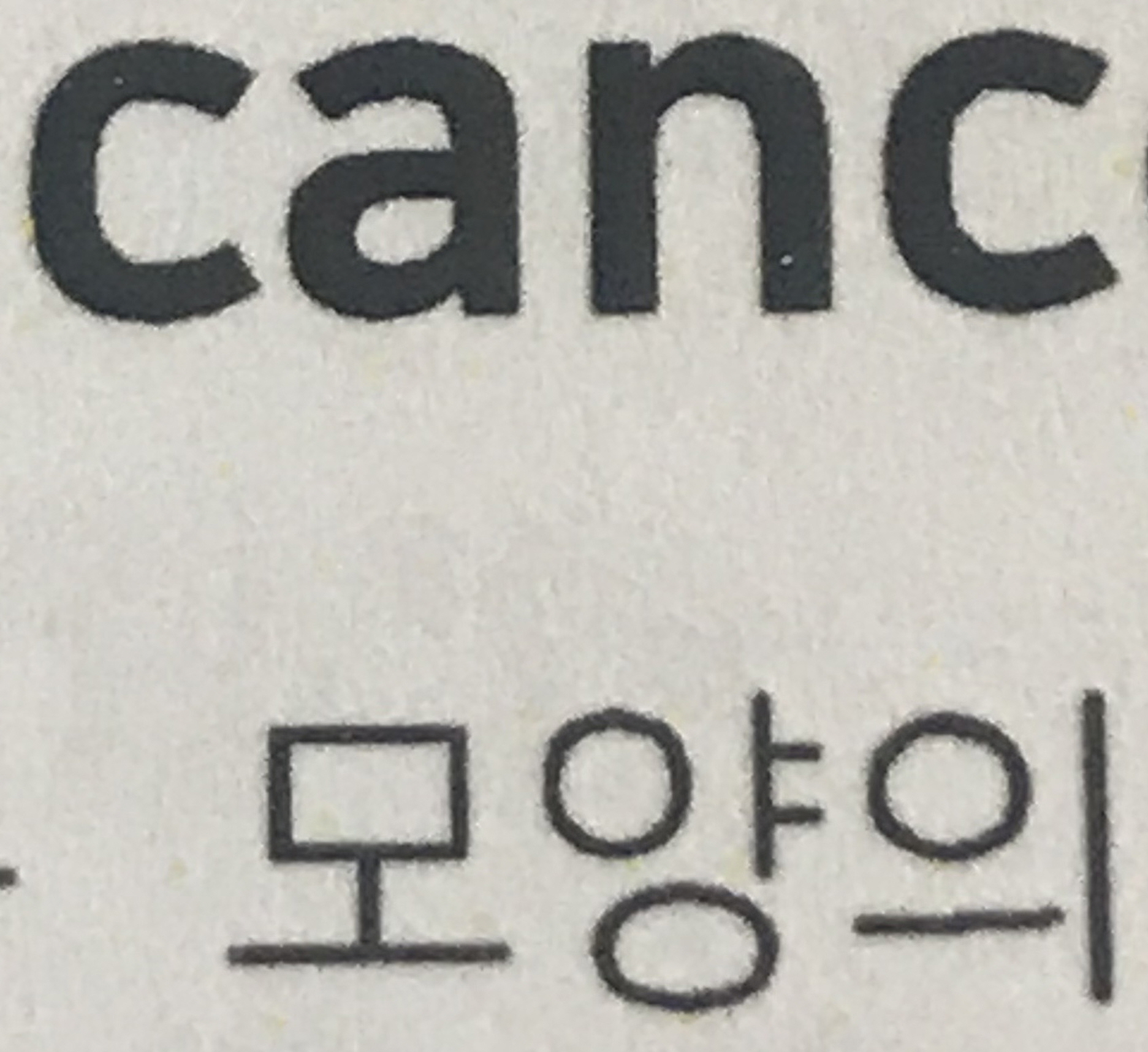
이거 폰트 kyl*** 2023.12.29 이거 무슨 폰트인가요ㅠㅠ 가독성이 좋아보이고 레포트 작성하는 데 너무 깔끔해서 꼭 알고 싶어요... 다 비슷한 고딕들이라 찾기 어려울까요ㅠㅠ?? 나눔 고딕, 나눔스퀘어 같기도 하구요.... 댓글 0 등록 쉽고 빠르게 가장 비슷한 폰트를 알고 싶다면? 이미지로 검색하기
다 비슷한 고딕들이라 찾기 어려울까요ㅠㅠ?? 나눔 고딕, 나눔스퀘어 같기도 하구요....